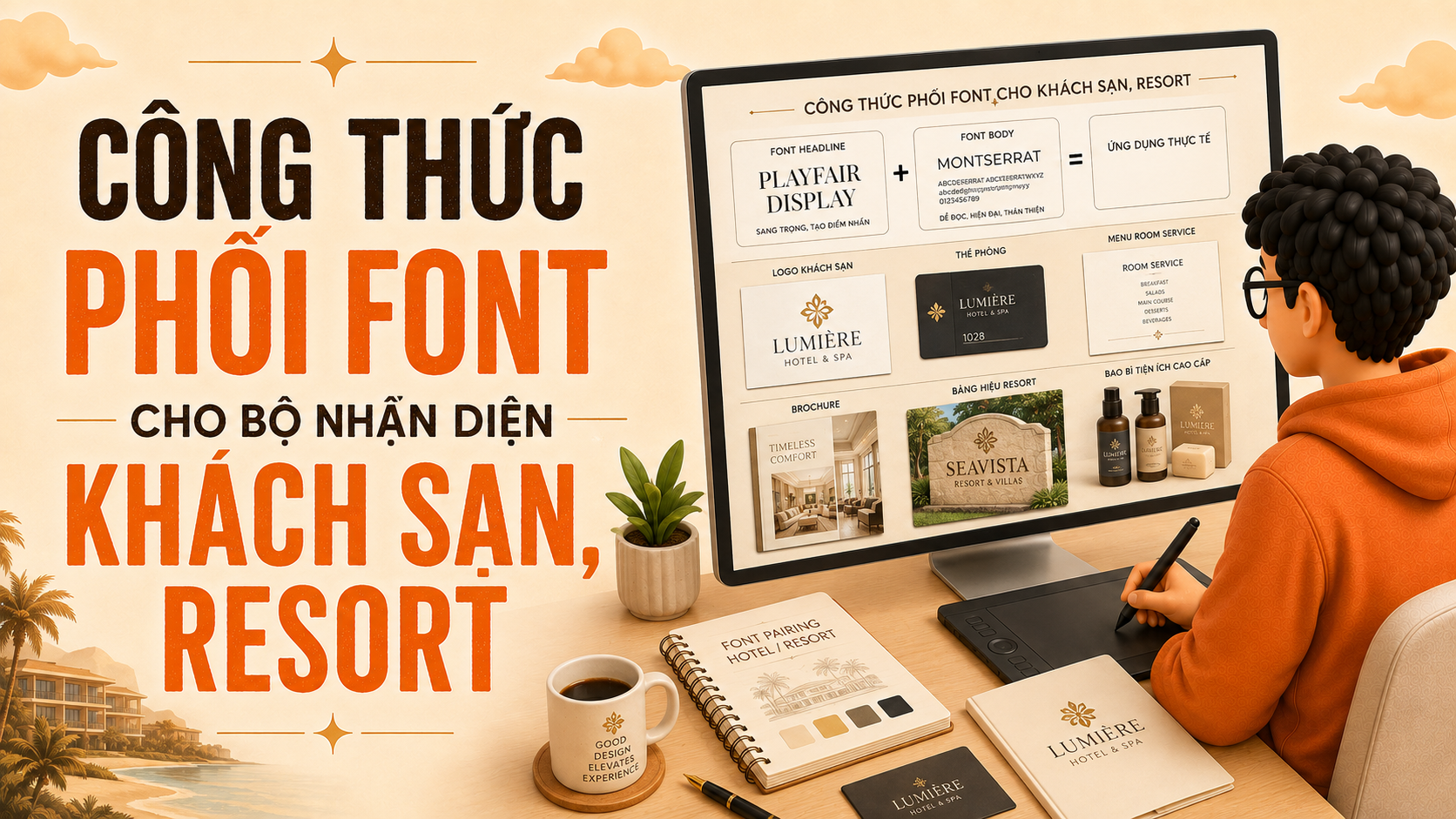
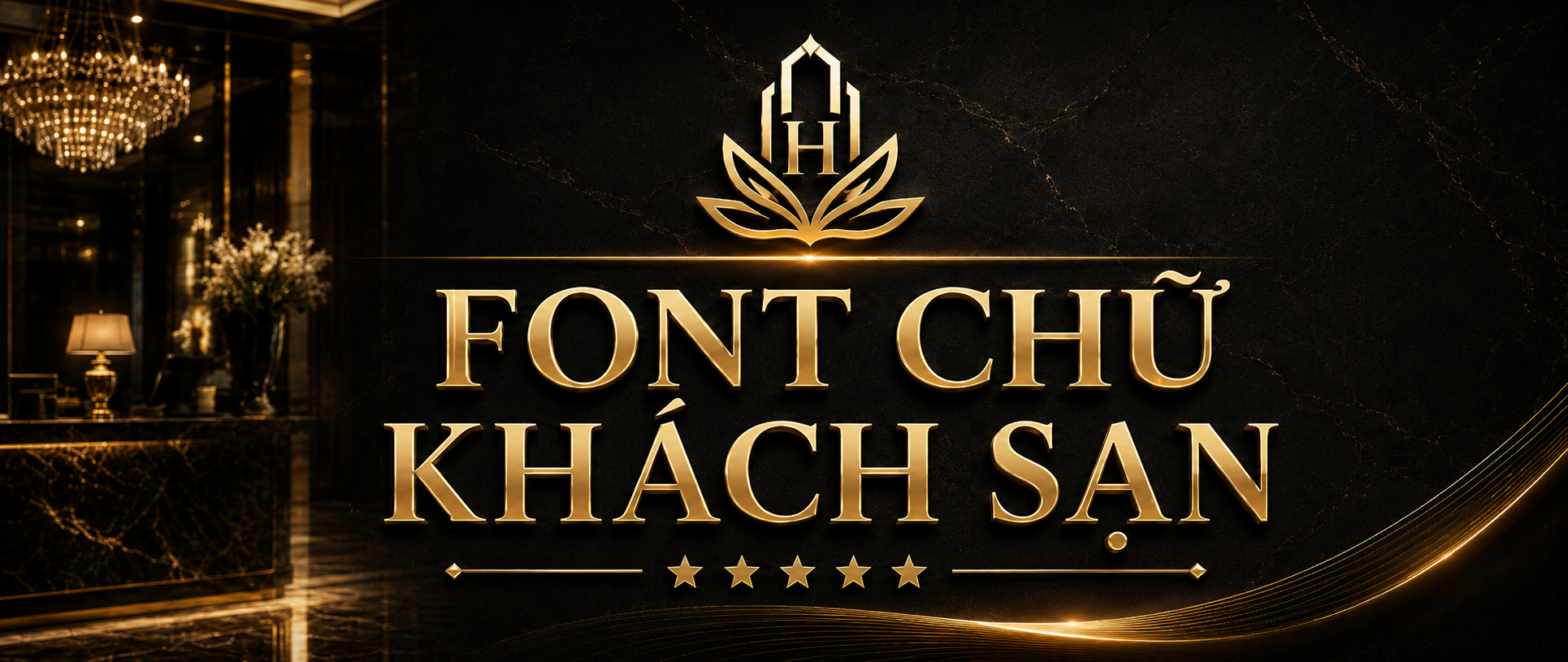
Khách sạn và resort là ngành mà typography ảnh hưởng trực tiếp đến cảm giác trải nghiệm. Trước khi khách bước vào sảnh, font trên logo, bảng hiệu, website, voucher, menu dịch vụ và booking banner đã gợi ra kỳ vọng: sang trọng, yên tĩnh, thiên nhiên, hiện đại, boutique hay nghỉ dưỡng cao cấp. Vì vậy, font chữ khách sạn, resort không chỉ cần đẹp mà còn phải đúng định vị.
Bài viết này gợi ý các font Việt hóa phù hợp trên Font S99 cho nhiều ngữ cảnh hospitality: logo hotel, boutique resort, signage, menu nhà hàng, spa, brochure, landing page đặt phòng, voucher và social campaign. Mỗi font được trình bày riêng một dòng với anchor Tải về để bạn dễ chọn và thử vào thiết kế thực tế.
Thiết kế khách sạn khác thiết kế bán hàng nhanh. Khách không chỉ nhìn giá phòng. Họ cảm nhận toàn bộ trải nghiệm: nơi này có yên không, có sạch không, có đáng tiền không, có cao cấp không, có hợp kỳ nghỉ của mình không. Font chữ góp một phần rất lớn vào cảm giác đó.
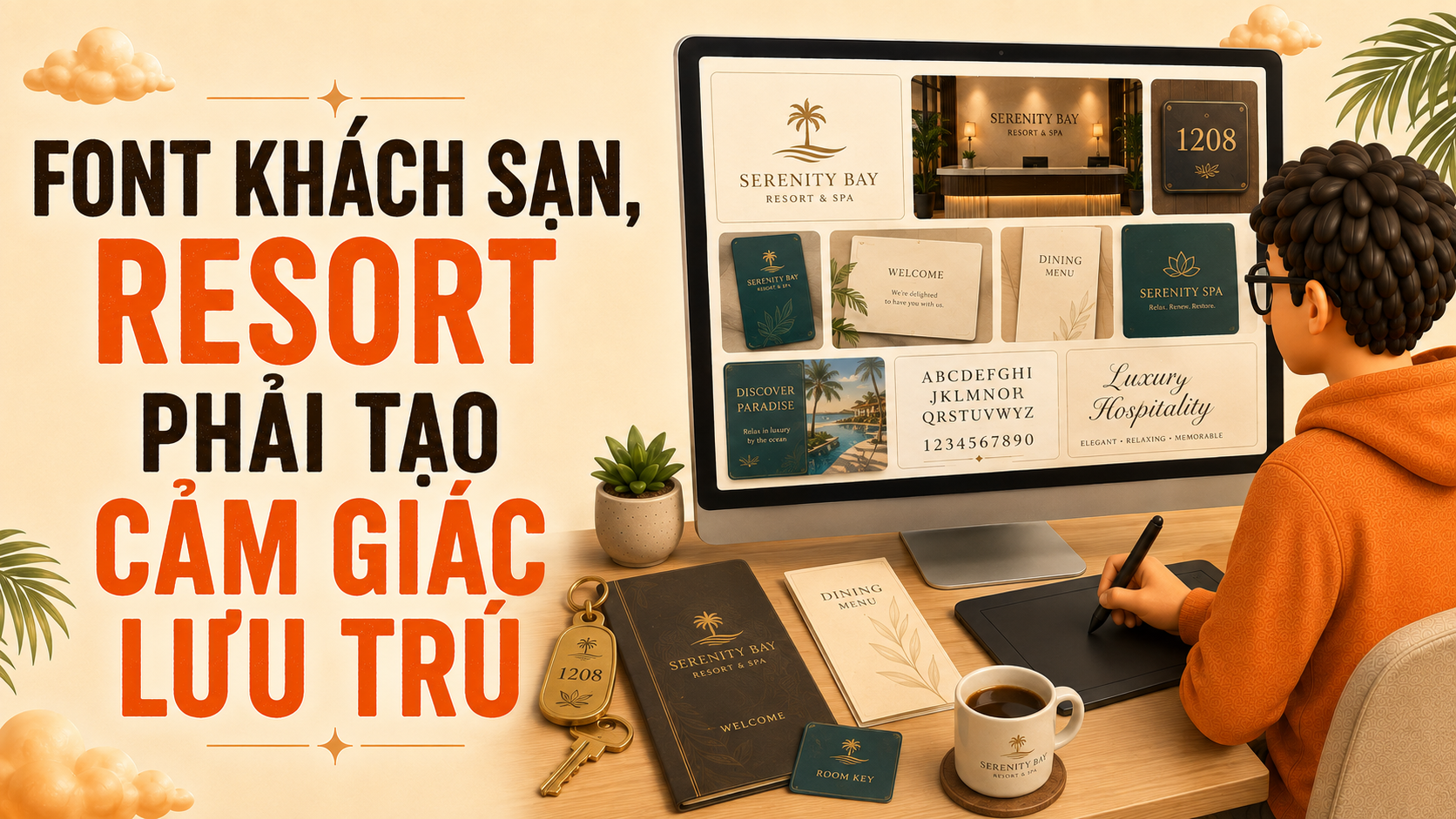
Một font serif thanh lịch có thể làm boutique hotel nhìn có gu hơn. Một sans-serif sạch giúp signage và thông tin phòng dễ đọc hơn. Một script mềm có thể hợp resort biển, spa hoặc gói nghỉ dưỡng lãng mạn. Nhưng nếu dùng sai chỗ, thiết kế dễ trở nên rối: logo thì khó đọc, bảng chỉ dẫn thiếu rõ, menu dịch vụ nhìn không chuyên nghiệp.
Với tiếng Việt, khách sạn và resort càng cần font Việt hóa tốt. Các cụm như nghỉ dưỡng ven biển, phòng hướng vườn, ưu đãi cuối tuần, dịch vụ spa, đặt phòng hôm nay có nhiều dấu. Font lỗi dấu sẽ làm bộ nhận diện mất điểm ngay cả khi hình ảnh rất đẹp.
Logo khách sạn cần nhận diện rõ, đủ sang và đọc được từ xa. Nếu là resort cao cấp, có thể dùng serif hoặc luxury sans-serif. Nếu là city hotel hiện đại, sans-serif sạch sẽ an toàn hơn.
Signage cần ưu tiên độ đọc. Tên tầng, số phòng, nhà hàng, spa, lễ tân, hồ bơi, thang máy, nhà vệ sinh và khu vực đỗ xe nên dùng font rõ, ít trang trí.
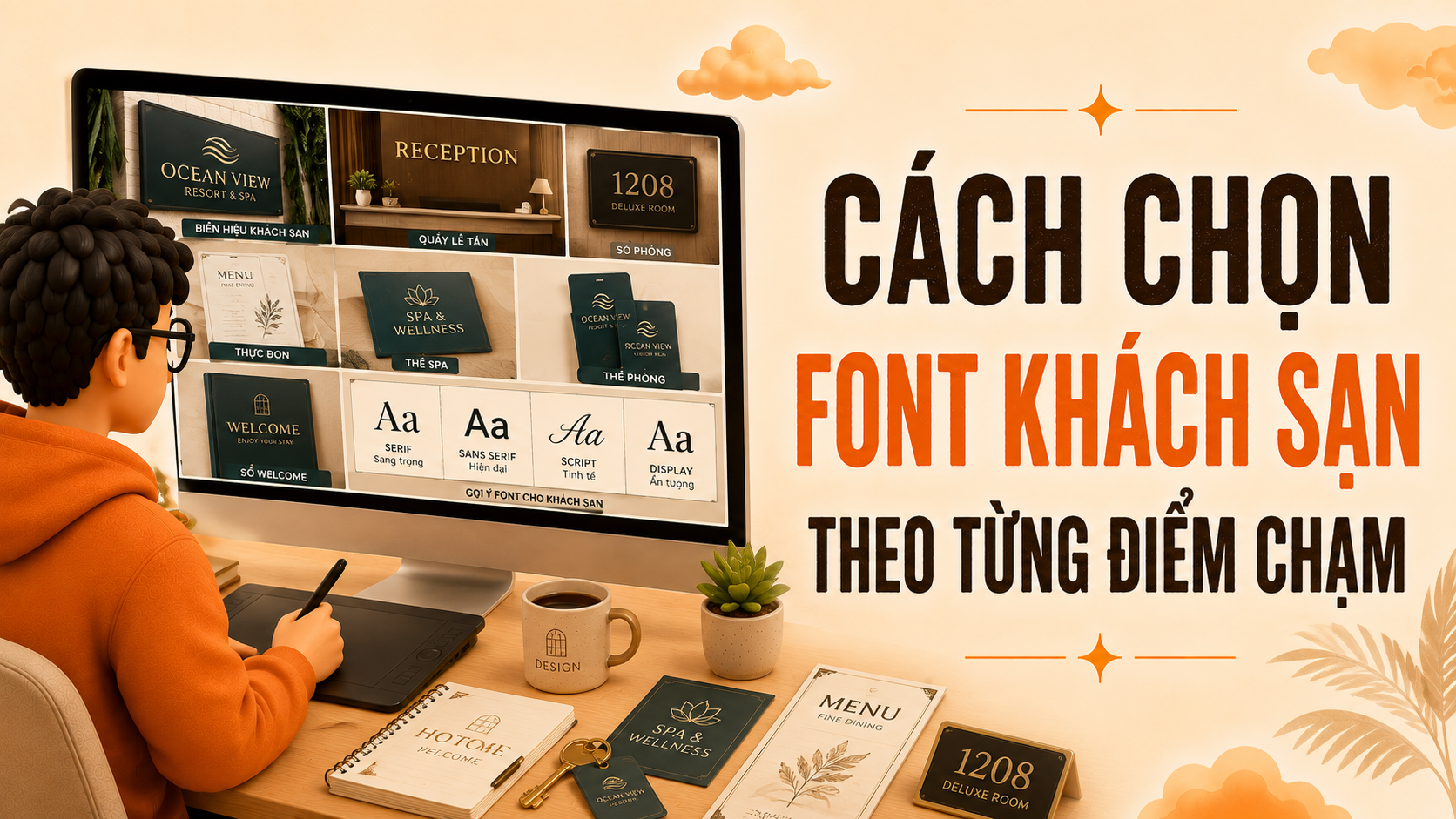
Brochure và website cần vừa có cảm xúc vừa dễ đọc. Headline có thể sang hơn, nhưng mô tả phòng, tiện ích, chính sách đặt phòng và CTA nên dùng font sạch.
Menu dịch vụ khách sạn cần font đủ trang nhã nhưng không làm khách khó đọc giá, món, liệu trình, giờ phục vụ hoặc điều kiện sử dụng voucher.
Serif là lựa chọn rất hợp với khách sạn cao cấp, boutique hotel, villa nghỉ dưỡng, resort biển, resort núi và thương hiệu hospitality cần cảm giác có chiều sâu. Nhóm font này hợp với logo, headline brochure, tên phòng, tên villa, tên nhà hàng và các ấn phẩm định vị thương hiệu.
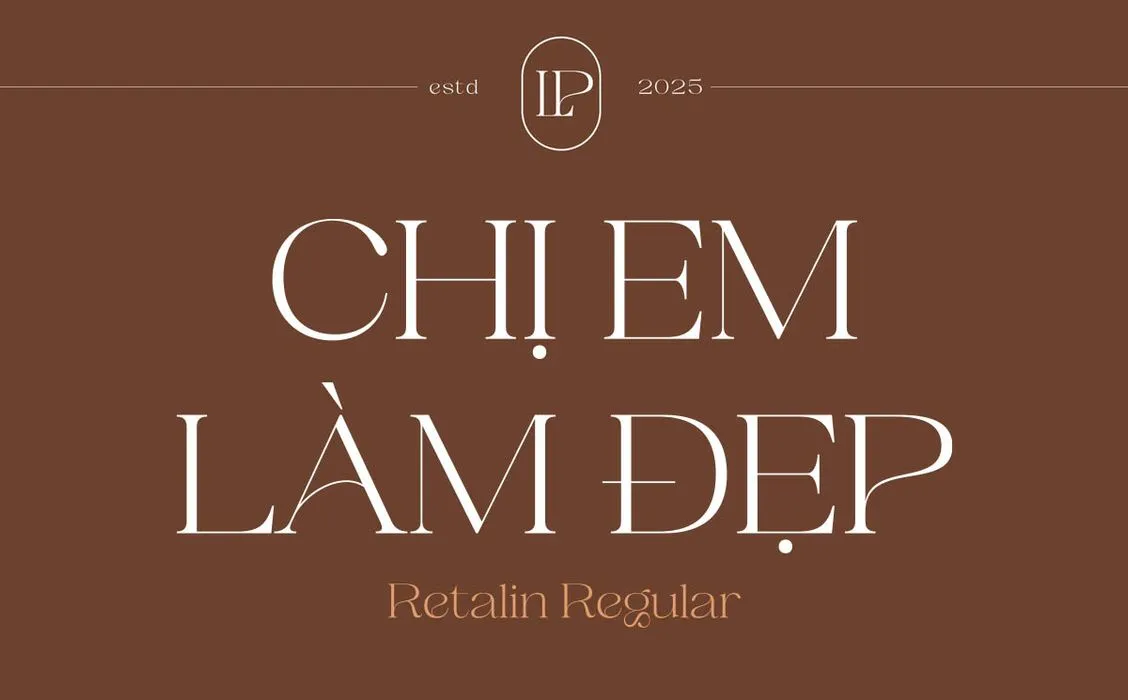
Khi dùng serif cho khách sạn, hãy để nhiều khoảng trắng và tránh hiệu ứng quá dày. Serif đẹp nhất khi đi cùng ảnh kiến trúc, phòng ngủ, hồ bơi, biển, núi hoặc texture giấy cao cấp. Nếu dùng cho logo, hãy kiểm tra cả bản ngang, bản dọc và favicon nhỏ.
Nhóm font này đặc biệt hợp với các concept như heritage hotel, boutique stay, private villa, luxury retreat, garden resort hoặc wellness resort. Với bảng chỉ dẫn, vẫn nên phối thêm sans-serif rõ để khách đọc nhanh hơn.
Sans-serif là nhóm không thể thiếu trong hệ thống khách sạn. Dù logo có dùng serif hay script, signage và thông tin vận hành vẫn cần font rõ. Đây là nhóm phù hợp với website, app booking, bảng chỉ dẫn, profile dịch vụ, chính sách nhận phòng, menu tiện ích và nội dung social.
Font TH Namian Sans Serif - Tải về
Font TH Manisans - Tải về
Font TH Artega - Tải về
Font TH Ervha Regular - Tải về
Font TH Teknaf - Tải về
Font TH Legacy Sans - Tải về
Font Montserrat Việt hóa - Tải về
Nhóm font này nên dùng cho phần cần đọc nhanh: phòng deluxe, phòng family, check-in, check-out, buffet sáng, đưa đón sân bay, hồ bơi, spa, nhà hàng, hotline và CTA đặt phòng. Nếu thiết kế trên mobile, hãy thử font ở kích thước nhỏ trước khi chốt.
Một hệ thống hospitality chuyên nghiệp thường dùng sans-serif làm nền vận hành. Font này không cần quá nổi, nhưng phải ổn định, sạch và dễ mở rộng trên nhiều tài liệu.
Một số resort hiện đại không muốn cảm giác cổ điển. Họ cần font sang nhưng gọn, hợp kiến trúc tối giản, villa biển, spa hotel, wellness retreat hoặc boutique resort phong cách châu Âu hiện đại. Luxury sans-serif giúp thương hiệu nhìn cao cấp mà vẫn sạch.
Font TH Luxury 7 - Tải về
Font TH Luxury 8 - Tải về
Font TH TOP LUXURY - Tải về
Font TH Carline Regular - Tải về
Font TH Bevas - Tải về
Font TH Moglan - Tải về
Font TH Waking - Tải về
Nhóm này hợp với logo, tên gói nghỉ dưỡng, headline booking banner, voucher spa, brochure villa và social campaign. Hãy phối với màu be, trắng, nâu nhạt, xanh olive, xanh navy, đen hoặc vàng champagne để giữ cảm giác hospitality cao cấp.
Không nên dùng luxury sans-serif quá mảnh cho bảng chỉ dẫn ngoài trời hoặc chữ nhỏ. Nếu dùng trên signage, hãy chọn weight đủ rõ và tăng tương phản nền chữ.
Font chữ khách sạn, resort tốt phải gợi đúng cảm giác lưu trú: sang, sạch, yên, thân thiện hoặc nghỉ dưỡng cao cấp tùy định vị. Hãy dùng serif cho logo và thương hiệu có chiều sâu, sans-serif cho signage và thông tin vận hành, luxury sans-serif cho resort hiện đại, script cho điểm nhấn boutique hoặc honeymoon.